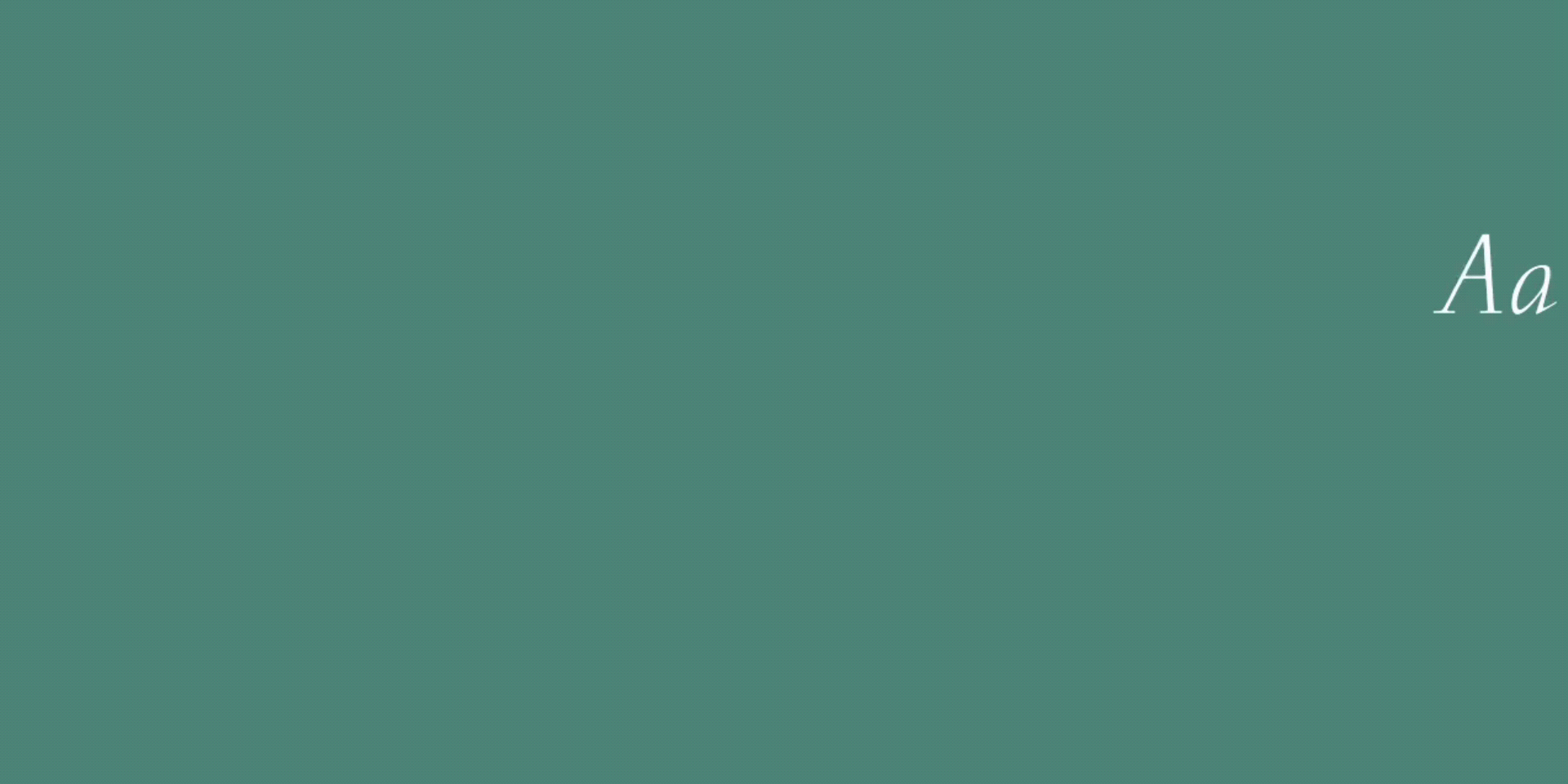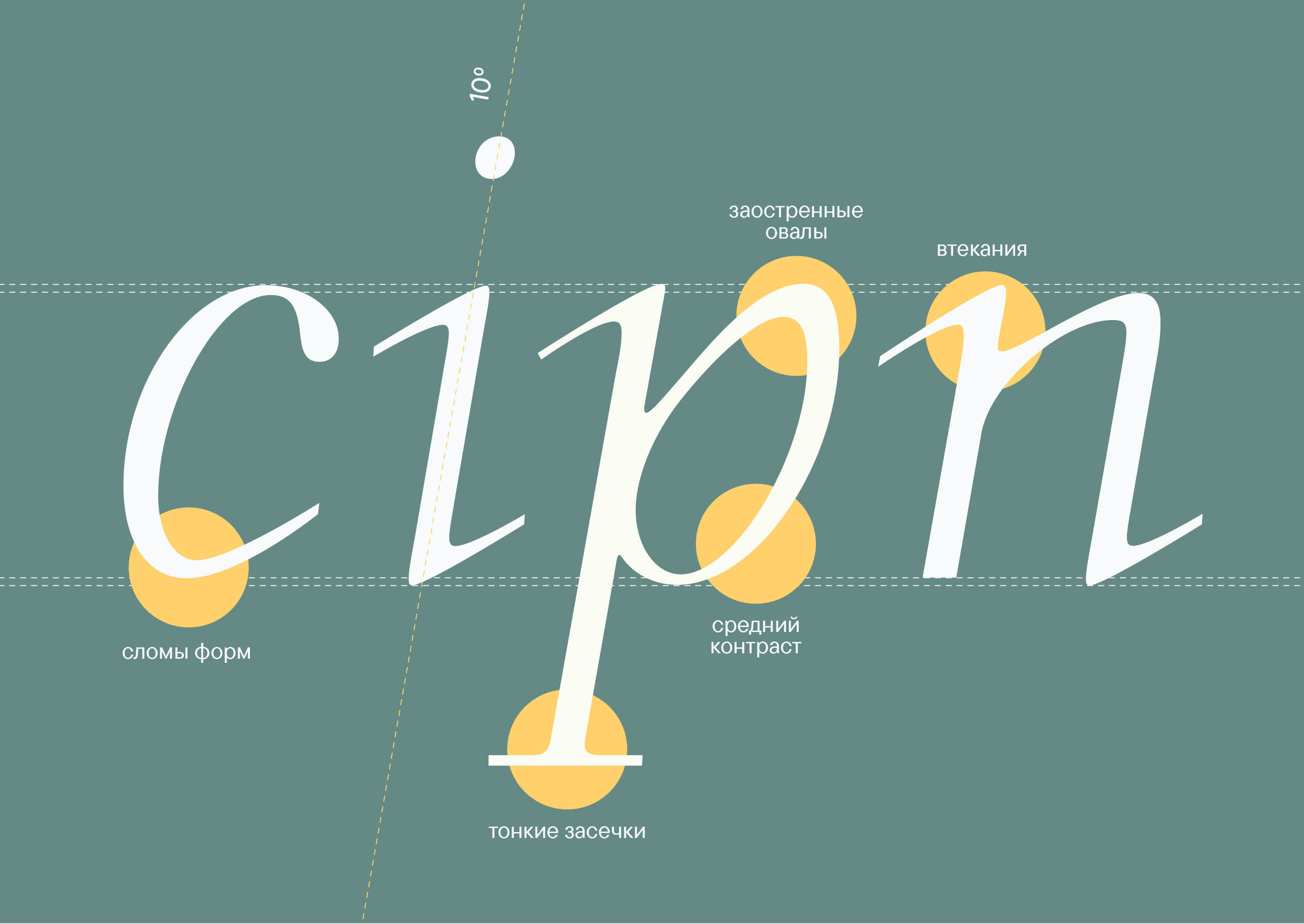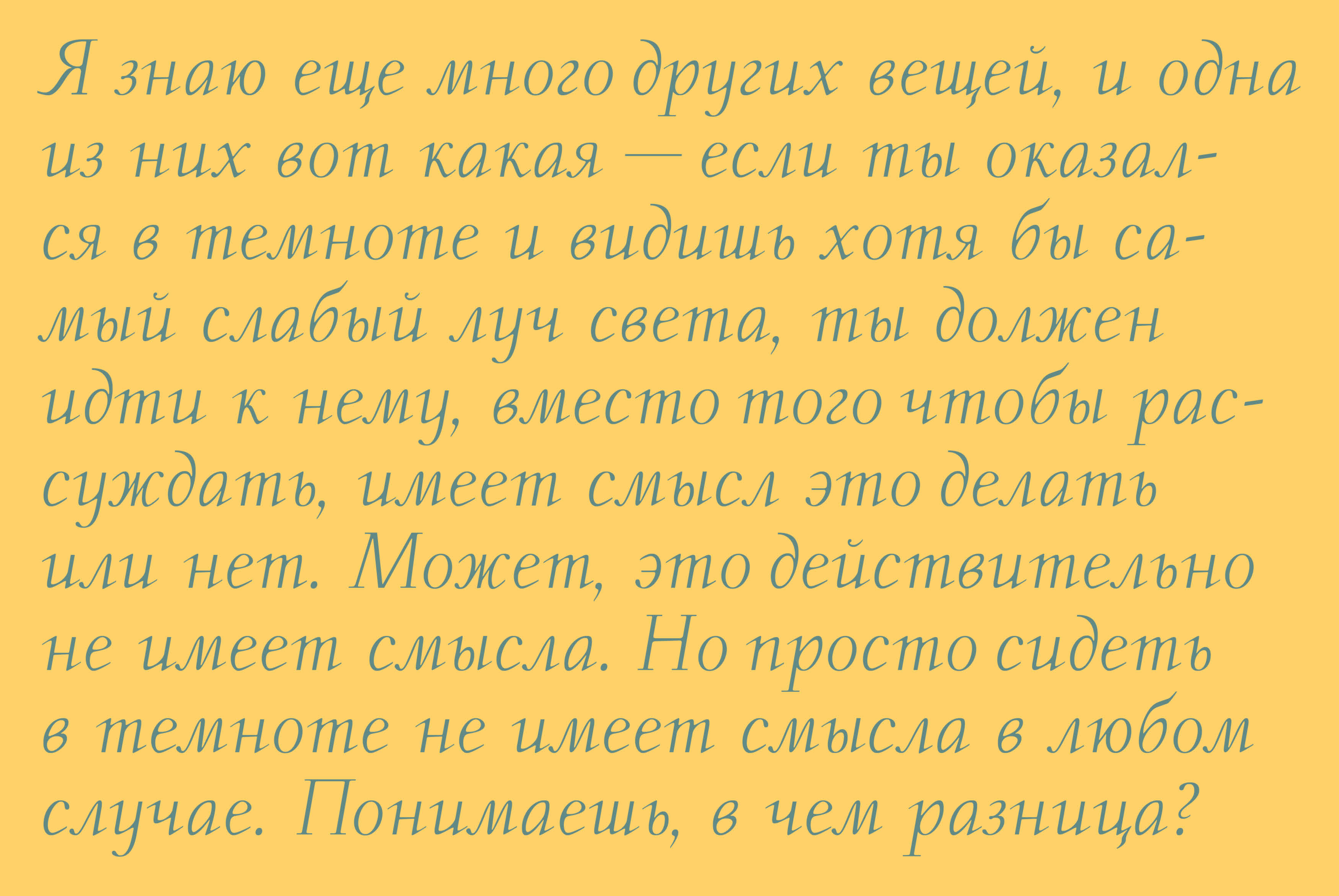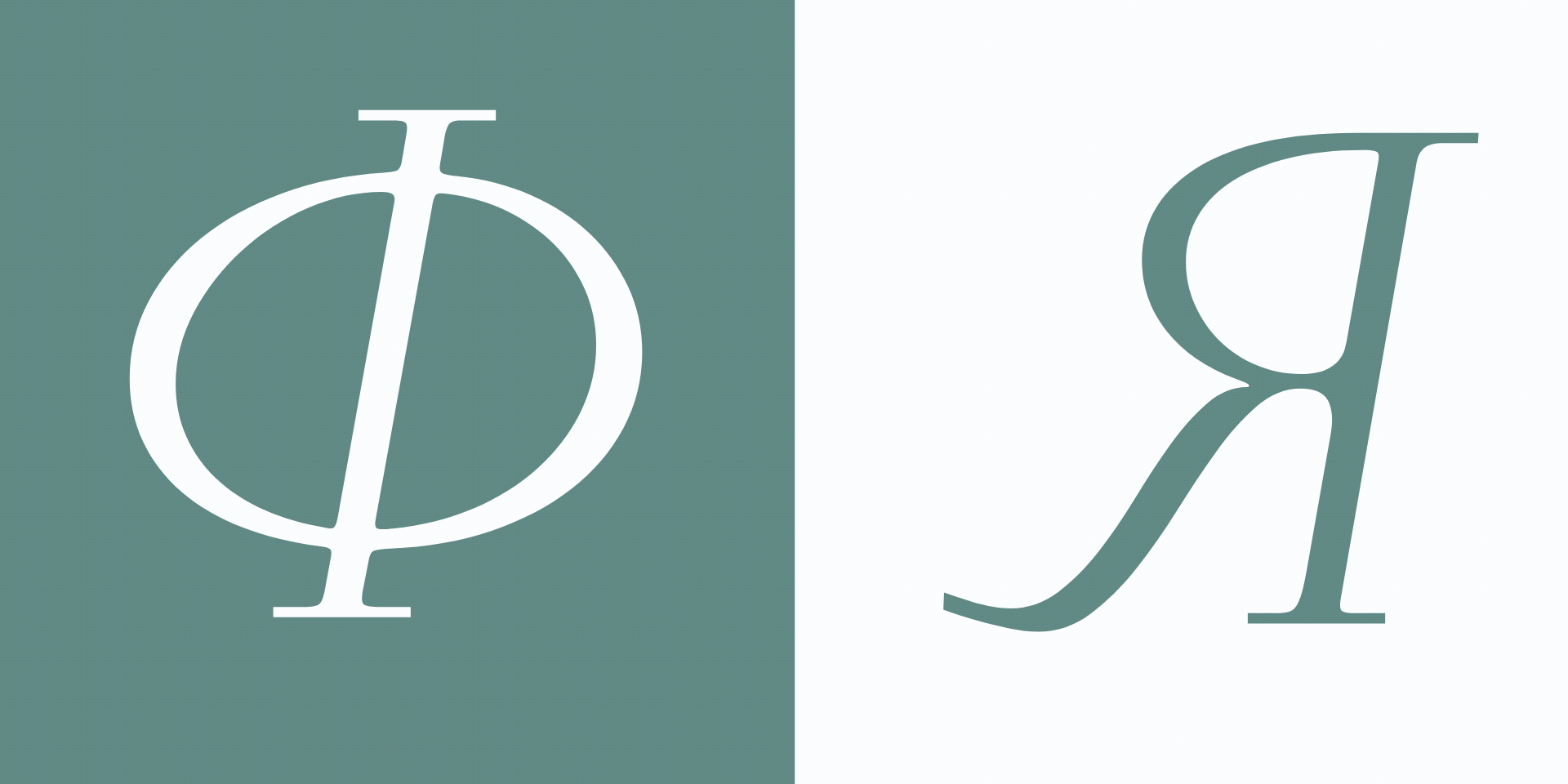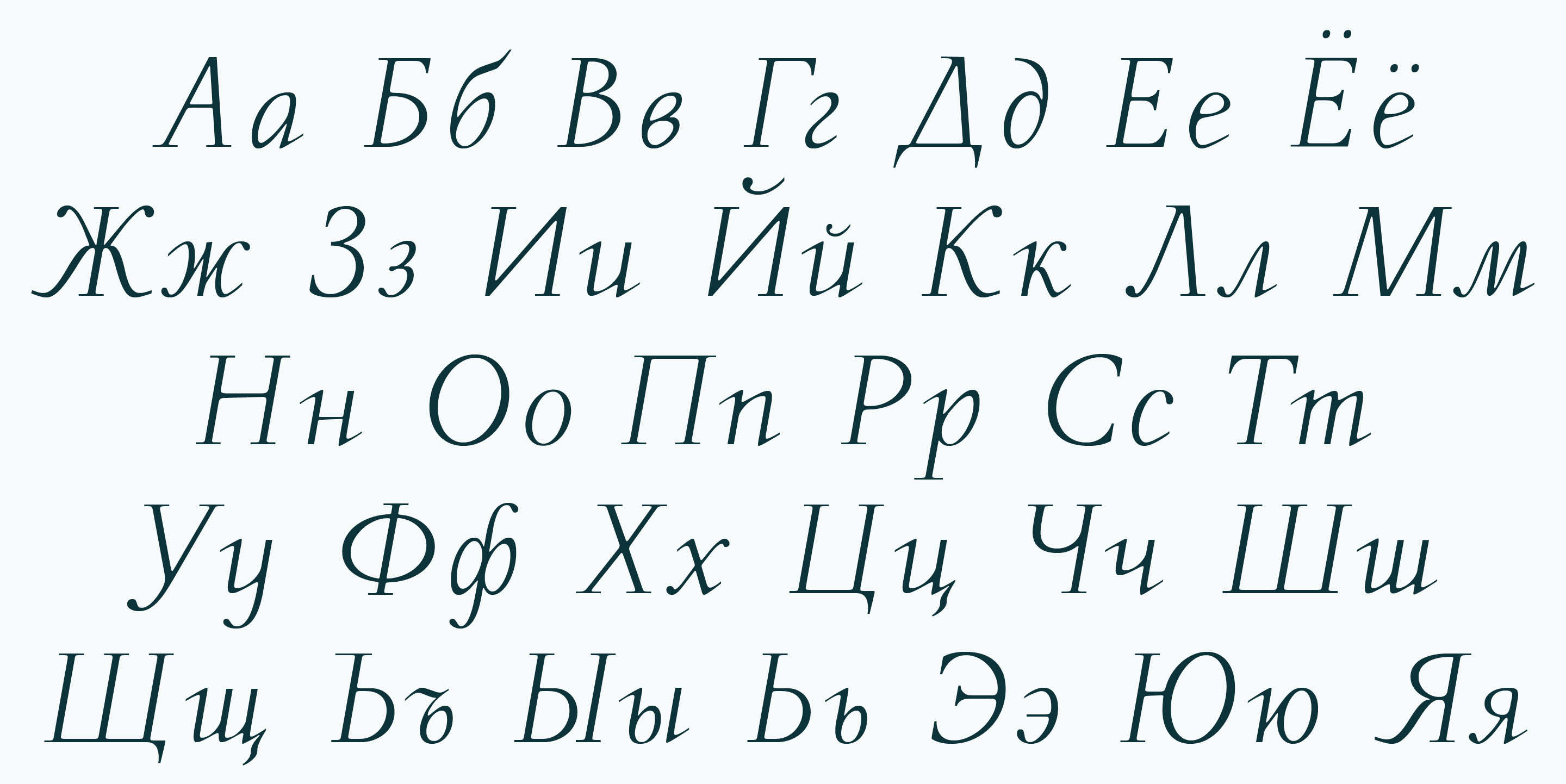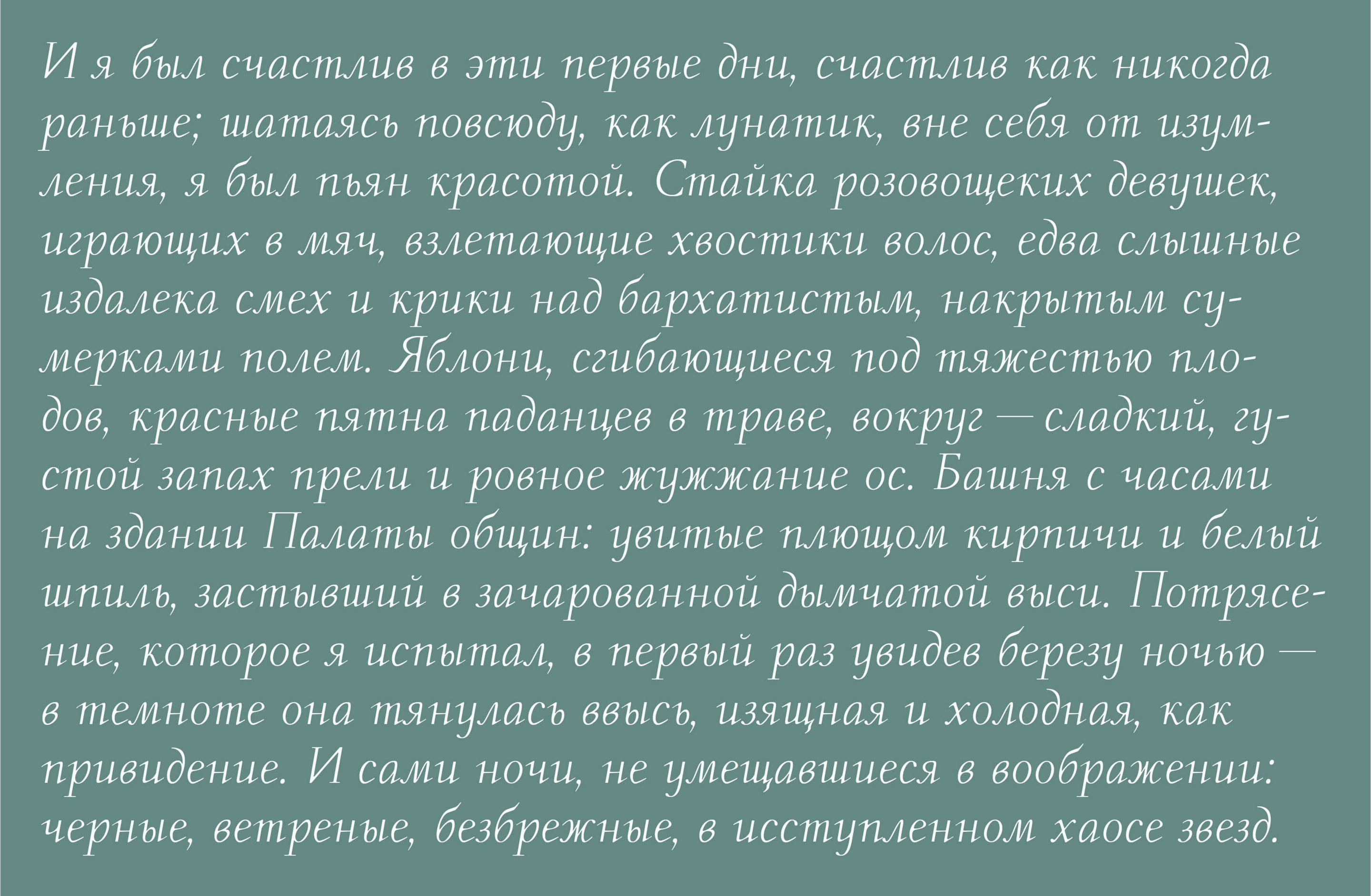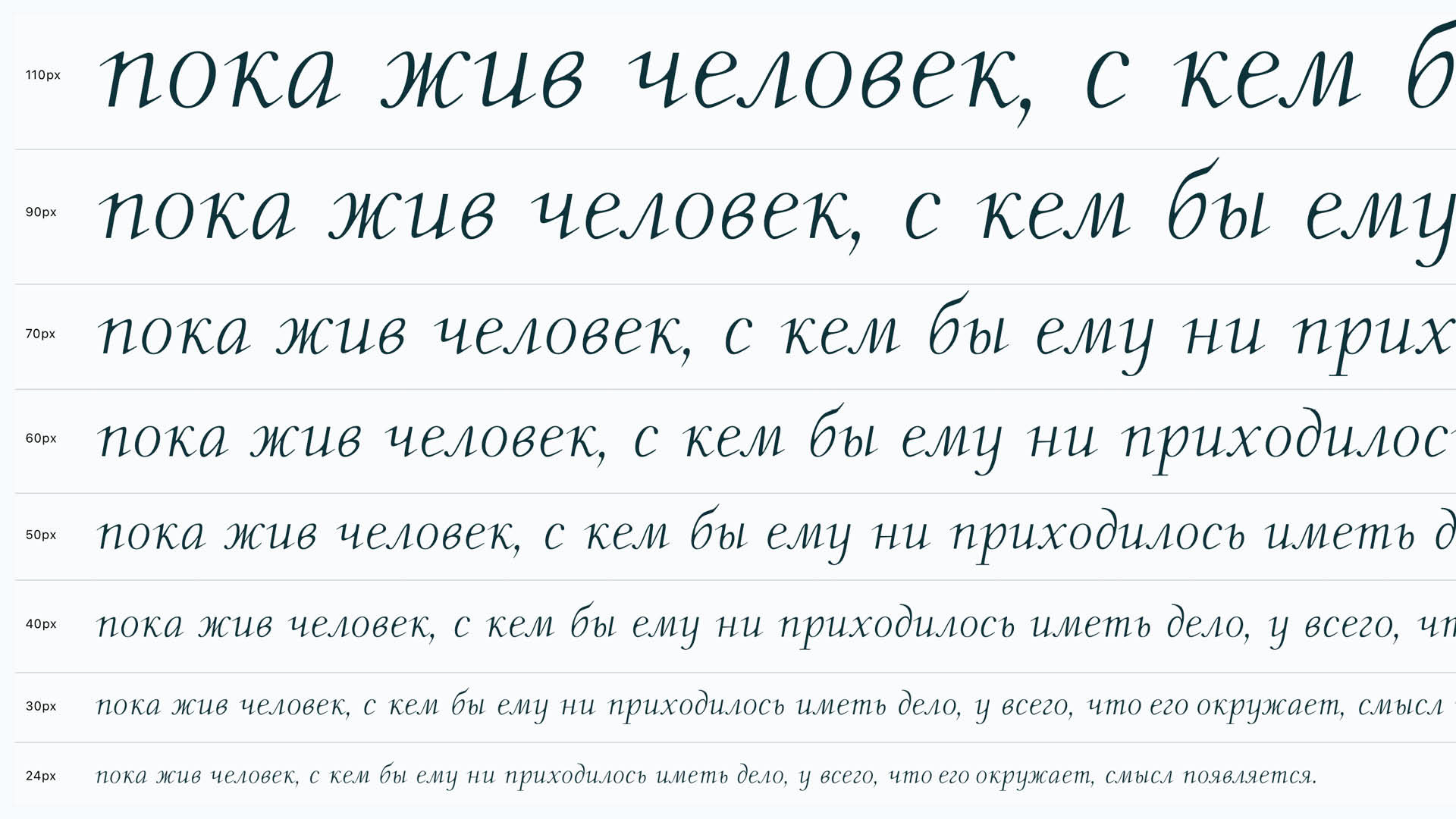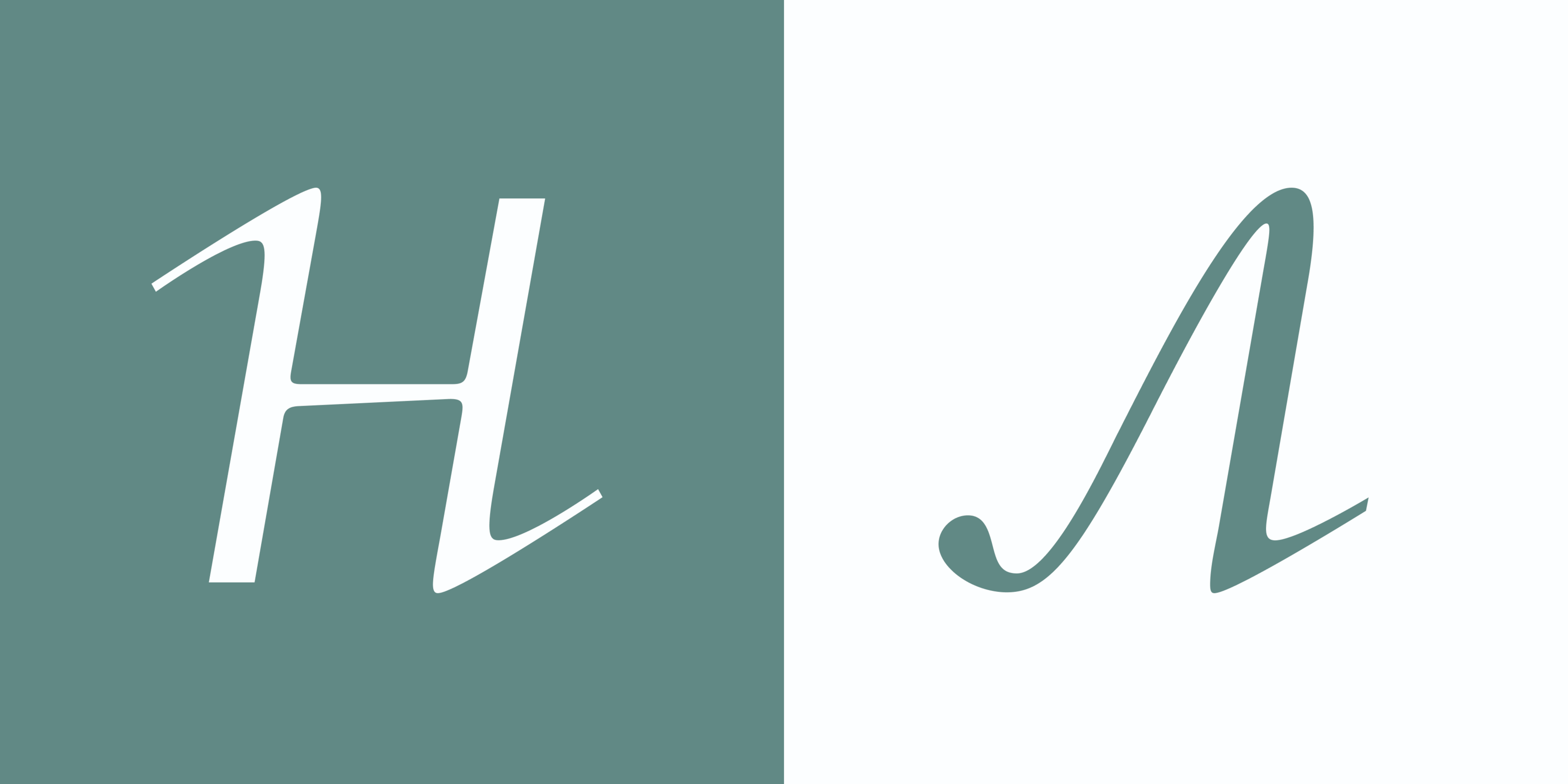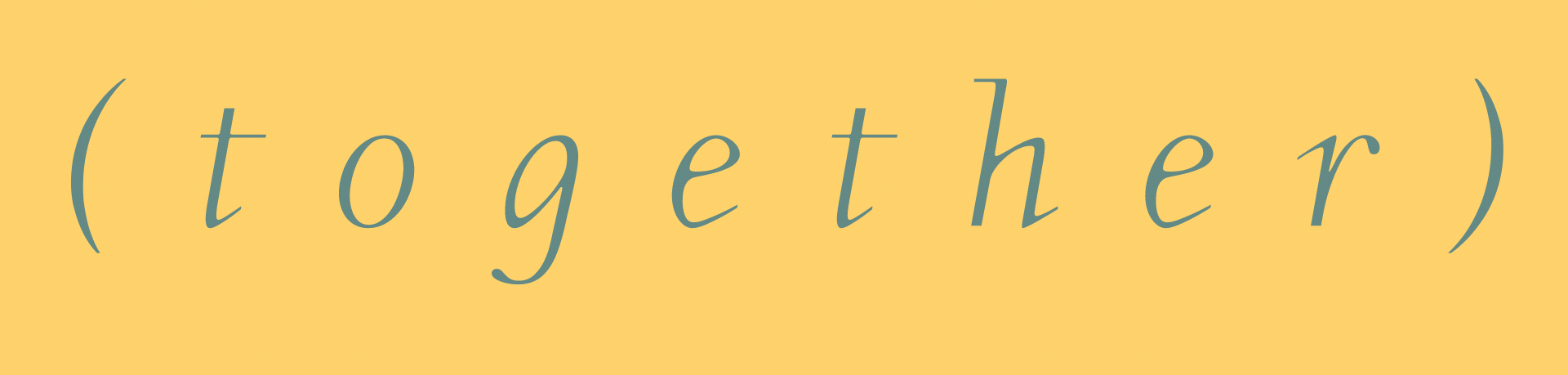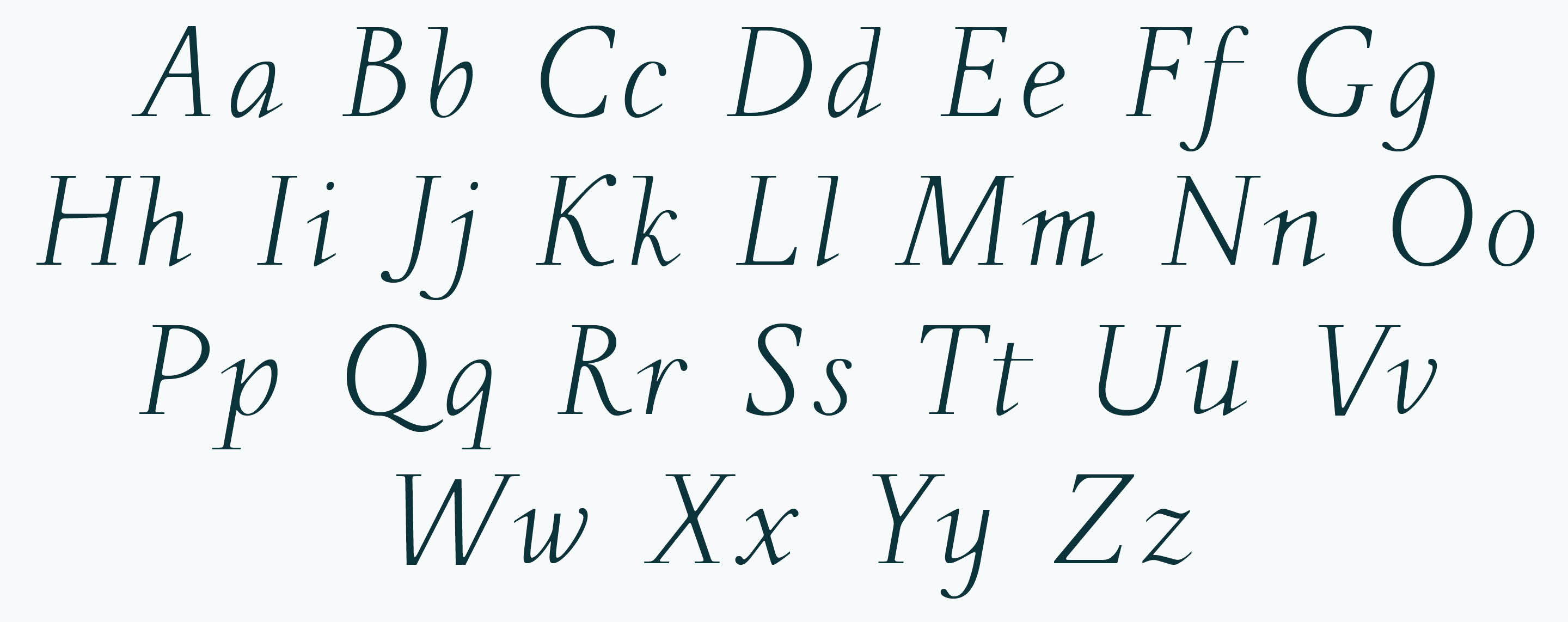
Halcyon font
Halcyon was inspired by French italic typefaces from the 16th and 17th centuries.
It features an old-style structure with long, almost straight serifs in the spirit of modern serif type, elegant swashes, and a pronounced contrast in the thickness of the serifs and additional strokes.
Halcyon — типографский курсив, вдохновленный французскими курсивными шрифтами XVI‑XVII веков. Он обладает старостильной структурой с длинными, почти прямыми засечками в духе новостильной антиквы, изящными залипами
и выраженным контрастом в толщинах засечек и дополнительных штрихов.